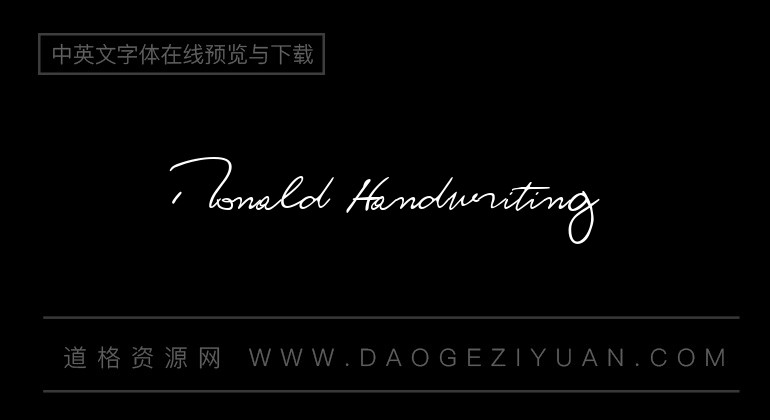
Ronald Handwriting
Ronald Handwriting字体是一种比较特殊的手写体字体,它的特点是具有比较柔和的线条,更具有温暖的感觉,适合用于排版的文字,它的字形具有比较柔和的曲线,使得文字更加柔和,更具有温暖的感觉,能够更好地表达出文字的内涵,它适用于商业文字、广告文字、书籍标题等。
Ronald Handwriting是一款非常不错的手写艺术字体,具有很好的视觉感,适合于文化类的宣传设计、商业类品牌的广告和产品包装设计以及个性化文字排版等较多场景。